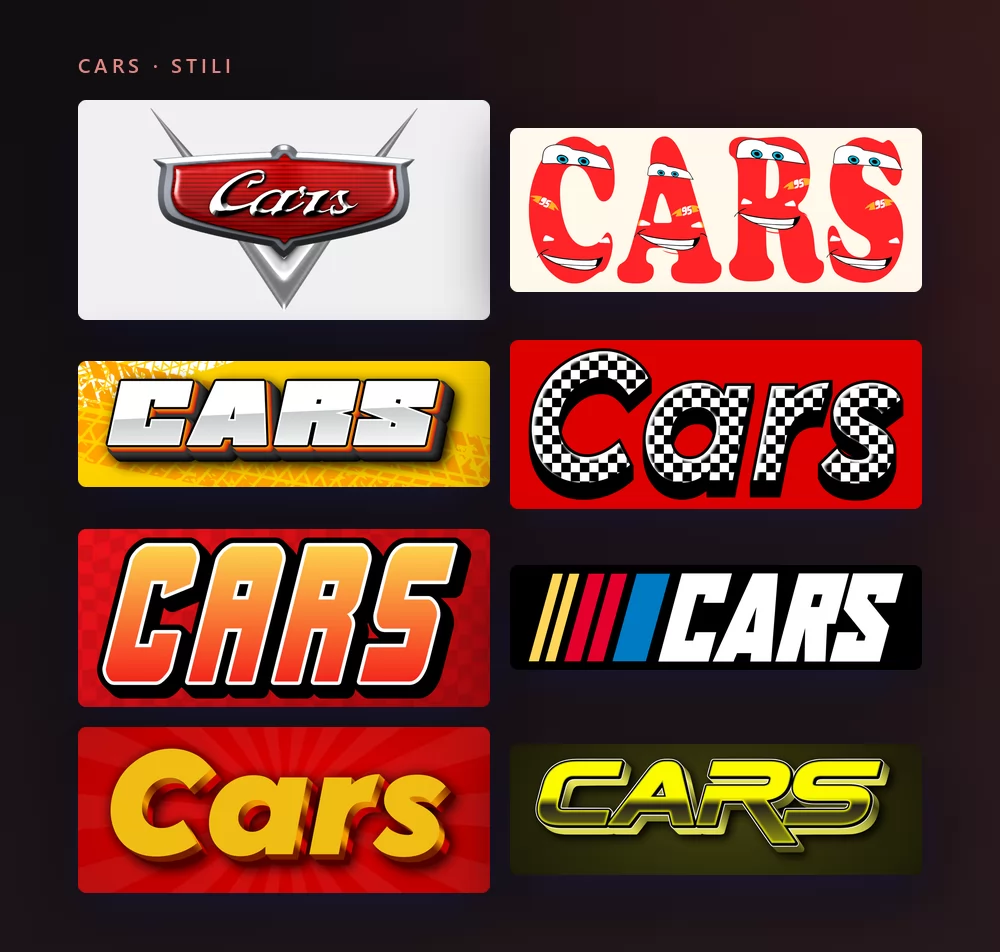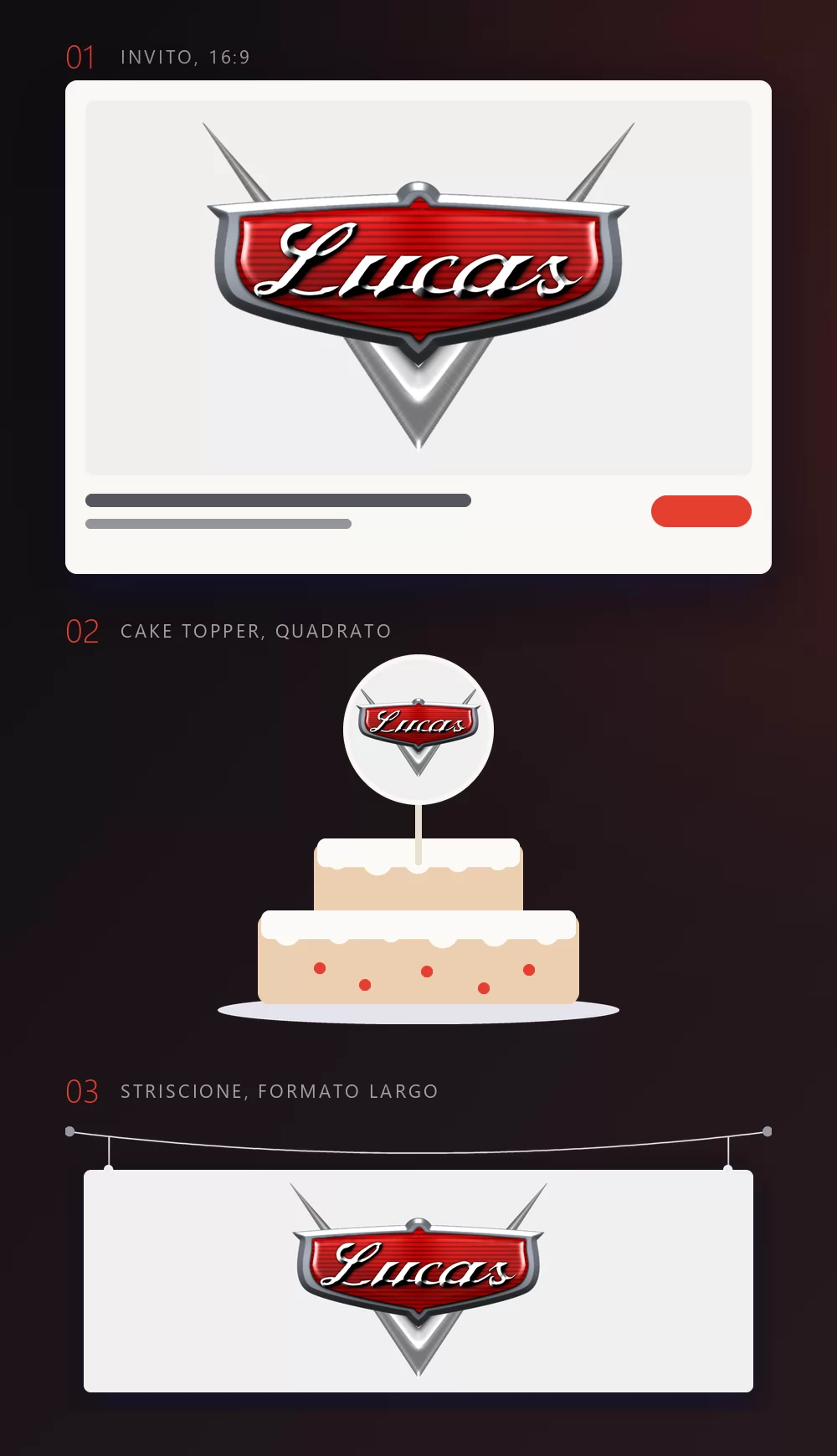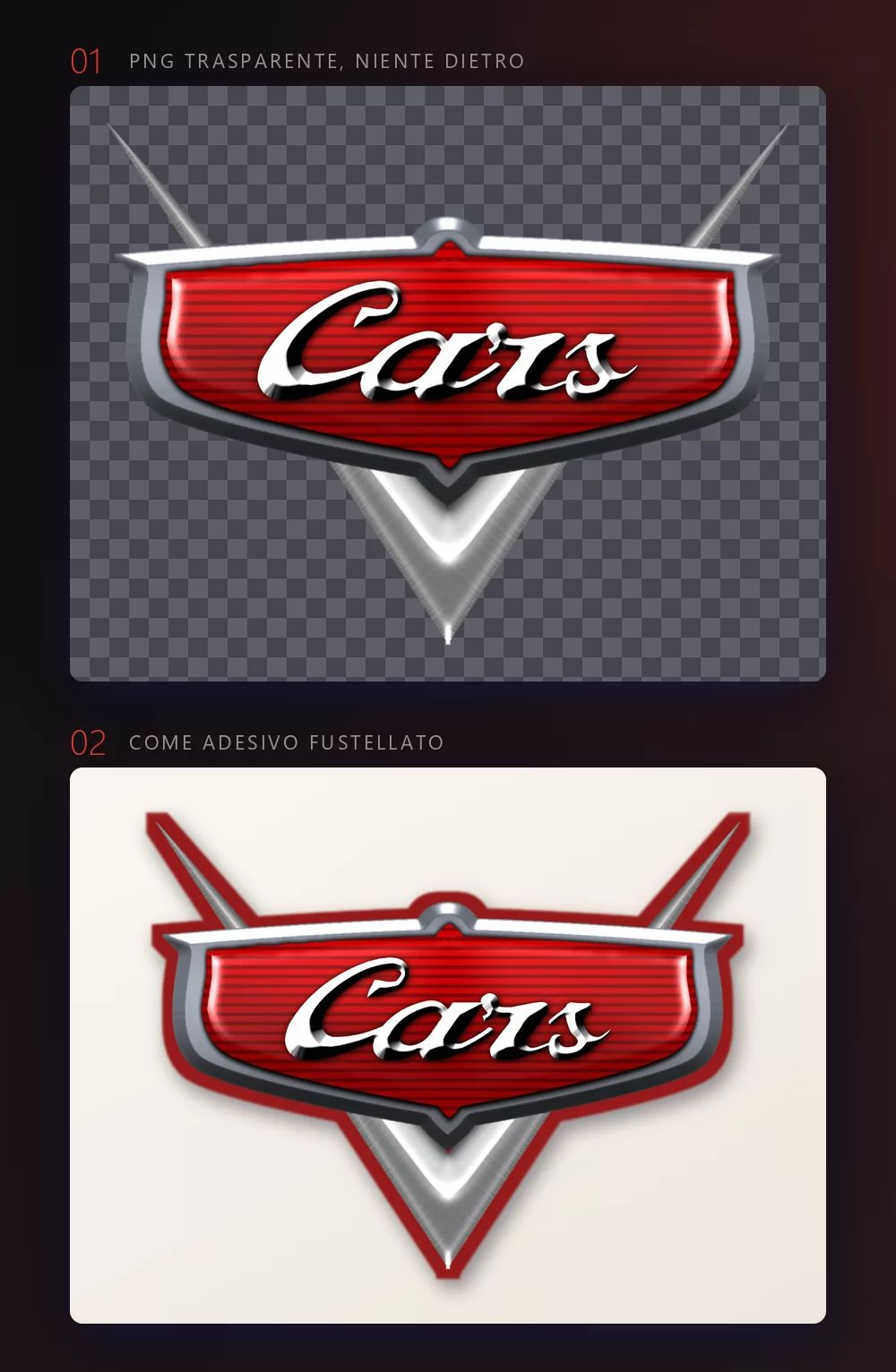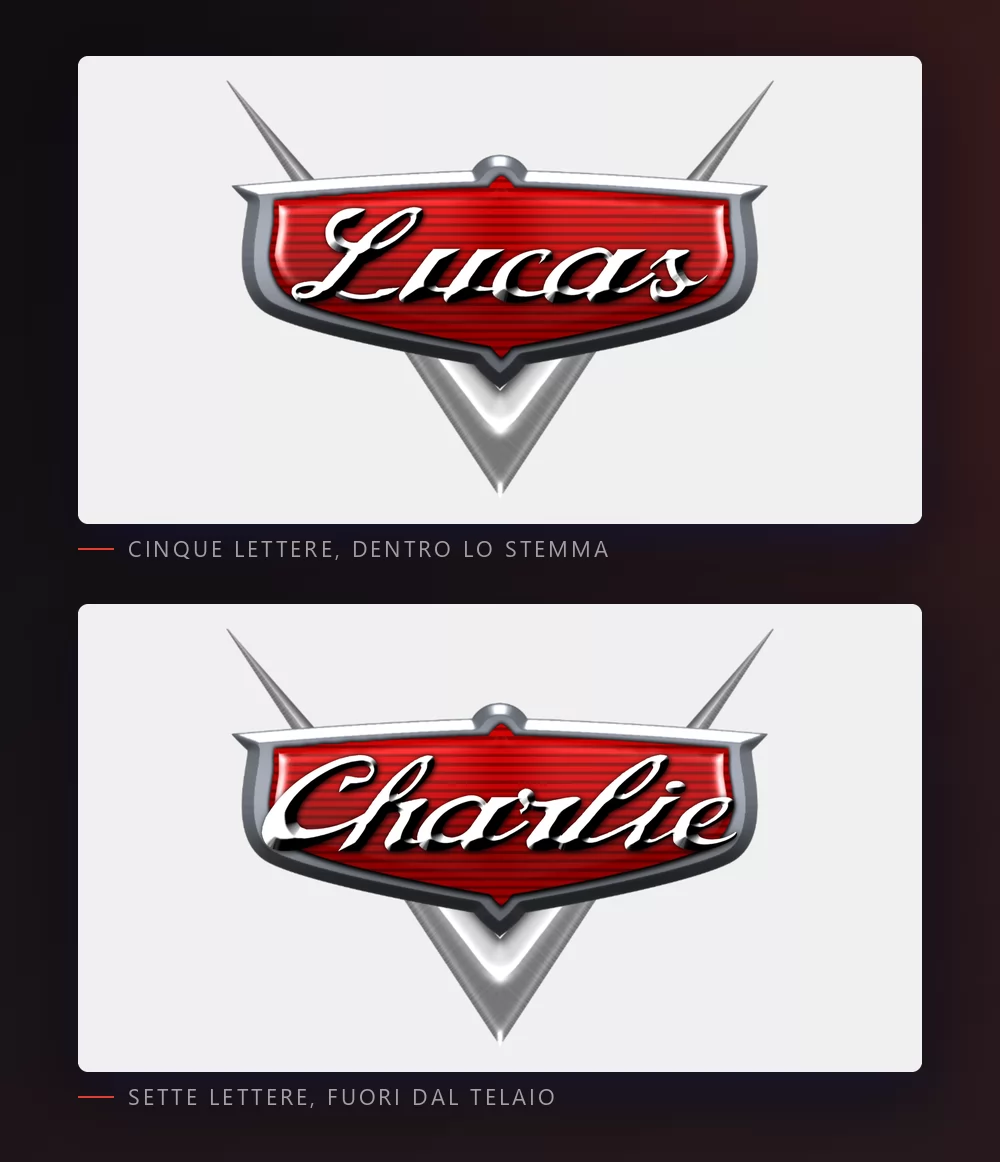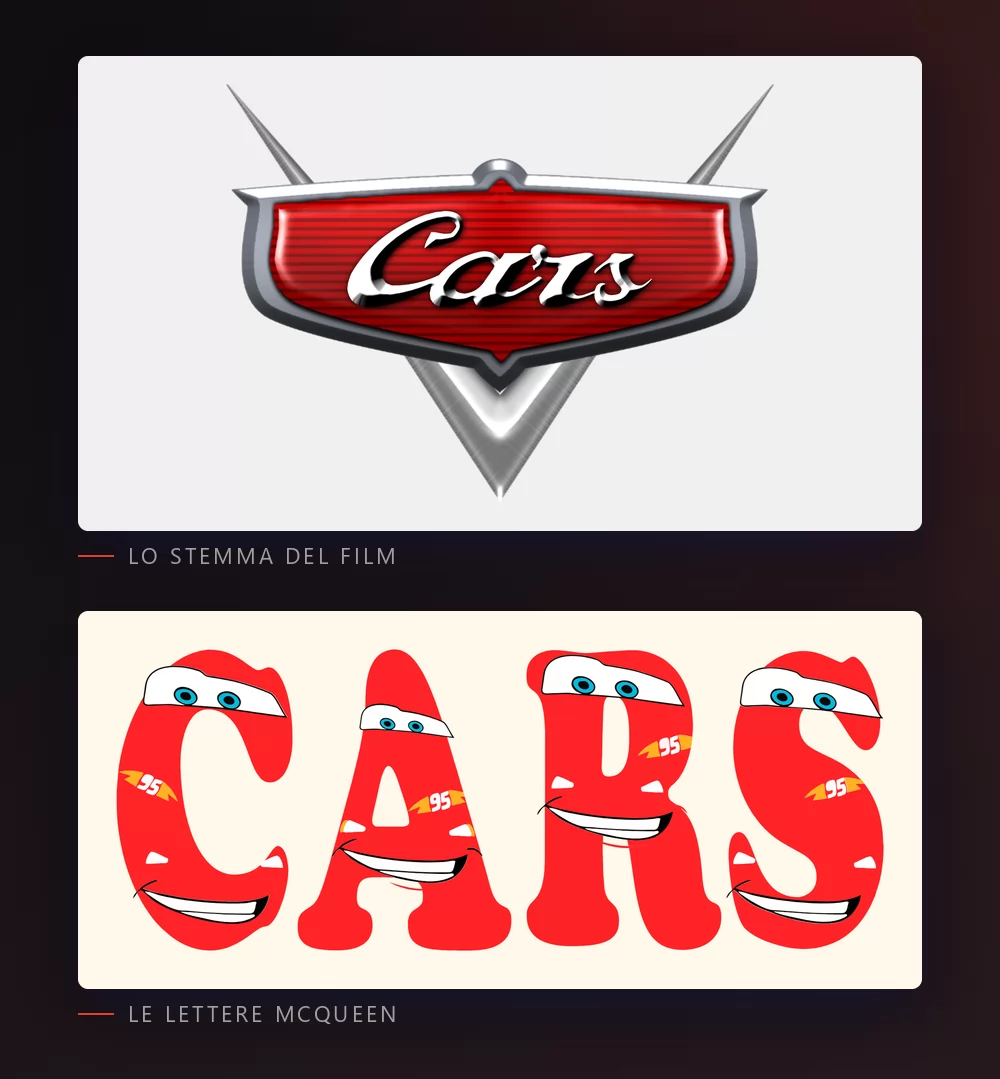
Il font di Cars, in breve
Cars è un film Pixar del 2006, una commedia in un mondo dove le automobili sono i personaggi. Il suo titolo non è scritto, è costruito: un lettering cromato dentro uno stemma, più vicino all'ornamento avvitato sul cofano di una berlina degli anni cinquanta che a una locandina.
Il lettering è molto vicino a Magneto Bold, disegnato da Leslie Cabarga e pubblicato da Font Bureau nel 1995. La pagina tipografica di Microsoft lo descrive come un richiamo alle "scritte in listello cromato posate sulle forme arrotondate delle porte dei frigoriferi e dei bauli delle auto degli anni quaranta e cinquanta", cioè esattamente l'epoca che il film cita.
Ed ecco quello che tutte le pagine di download si dimenticano. Magneto è un font commerciale, e il consiglio abituale è di andare a comprarlo. Ma Microsoft lo elenca tra i font che distribuisce, file Magnetob.ttf, e precisa che è disponibile nelle applicazioni Office. Se hai Microsoft Office sulla macchina, molto probabilmente hai già Magneto Bold installato, e da un pezzo.
Come fare un testo Cars
Passo 2. Scegli uno stile
Lo stile della pagina di destinazione è lo stemma: lettering cromato, smalto rosso, scudo argentato. Nella lista c'è anche tutto il lato corsa del film, bandiere a scacchi, tracce di pneumatico, strisce da gara, e le lettere con gli occhi di Saetta McQueen. La scheda "Stile" permette di cambiare riempimento, contorno e ombra in entrambi i casi.
Quante lettere stanno nello stemma
L'abbiamo misurato, perché è questo a decidere quale stile prendere. Lo scudo contiene comodamente cinque lettere. A sei, la prima e l'ultima toccano il filo argentato. A sette sono fuori, come qui sopra.
E a differenza di ogni altro stile, rimpicciolire il testo non serve: lo stemma cresce con la parola, quindi la proporzione resta la stessa. Per un nome più lungo la risposta non è un'impostazione ma un altro stile. Le maiuscole da corsa della stessa lista accettano qualsiasi lunghezza, non hanno un telaio da cui uscire.
Lo stemma, o le lettere McQueen
Lo stemma è la forma del logo del film: il lettering cromato su smalto rosso dentro lo scudo argentato. È quello che la gente ha in mente quando dice "il logo di Cars", ed è quello giusto per un nome su un invito.
Le lettere McQueen sono l'altra metà di ciò che si cerca: ogni lettera è una macchinina rossa, con gli occhi nel parabrezza e il fulmine 95 sulla fiancata. Parlano del personaggio più che del film, e funzionano meglio su uno striscione che rimpicciolite in una foto profilo.
Sono entrambi nella stessa lista: puoi provare un nome nell'uno e poi nell'altro senza lasciare la pagina.
Quale font installare, se ne vuoi uno
Magneto Bold è il font identificato, e il primo posto dove cercarlo è la tua macchina: arriva con Microsoft Office. Apri il menu dei font in Word e scrivi il nome. Se c'è, è fatta, e non hai comprato nulla.
Se non c'è, Magneto si compra da Font Bureau e dai suoi rivenditori. È una licenza commerciale vera, quindi le copie che girano sui siti di font gratuiti non sono legittime.
Per una licenza aperta, la scelta onesta è Alfa Slab One su Google Fonts, disegnato da JM Solé nel 2012 con licenza SIL Open Font. Sii chiaro su cosa ti dà e cosa no: è un egiziano, quindi porta il peso e la sicurezza, non lo svolazzo. È quello che diversi altri generatori usano senza dirlo.
Nessuno di questi ti dà lo scudo. Lo stemma è una forma, non un font, ed è per questo che il generatore lo disegna attorno al tuo testo invece di chiederti di trovarlo.
A cosa serve davvero alla gente
Le feste di compleanno per prime, e di gran lunga: l'invito, lo striscione sopra il tavolo, il cake topper, il nome sulla porta della cameretta, il numero su una pista costruita in casa. Poi i cartelli sulla porta dell'aula, le miniature YouTube dei video di macchinine, e la maglietta stampata per una festa di famiglia. Quasi tutto questo riesce meglio con un PNG trasparente che con un font installato, perché quello che si riconosce è lo scudo e il cromo, e un file di font dà solo la forma delle lettere.